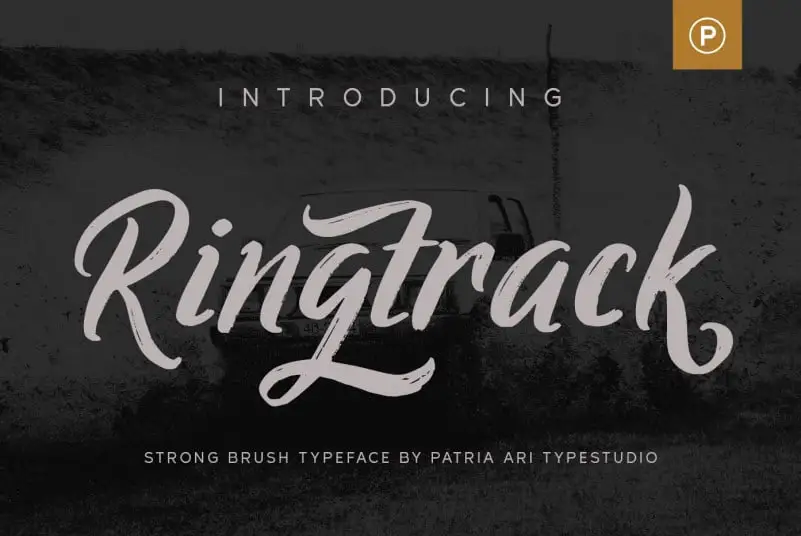
Ringtrack Script Font – Download Grátis
Aqui está uma breve descrição para a página de download da fonte ‘Ringtrack Script Font’, no estilo solicitado: Ringtrack Script é uma nova adição às opções de script fonts disponíveis, e suas qualidades se destacam na categoria. Esta fonte usa um traço firme e agudo, inspirado em esboços realizados a mão, que oferece swashes flexíveis para criar textos cheios de vida e expressão. Suas linhas fortes lembram as formas delicadas das letras escritas manualmente, criando uma harmonia única entre a força e o detalhe. O designer Patria Ari Typestudio trouxe à vida esta fonte com um toque único, oferecendo uma experiência de escrita fluida que não só valoriza sua versatilidade mas também proporciona ao design um toque de personalização. Esta é uma escolha perfeita para aqueles buscando adicionar profundidade e diversão aos seus projetos gráficos, seja em criação de logotipos, revistas ou até mesmo artesanato digital. Com swashes que podem ser facilmente adaptados ao texto, Ringtrack Script também se destaca como uma fonte ideal para designers criativos que valorizam o poder de expressão da letra. Esta é uma fonte que reflete a beleza e agilidade do design a mão, oferecendo aos designers o poder de moldar textos em sua própria imagem.